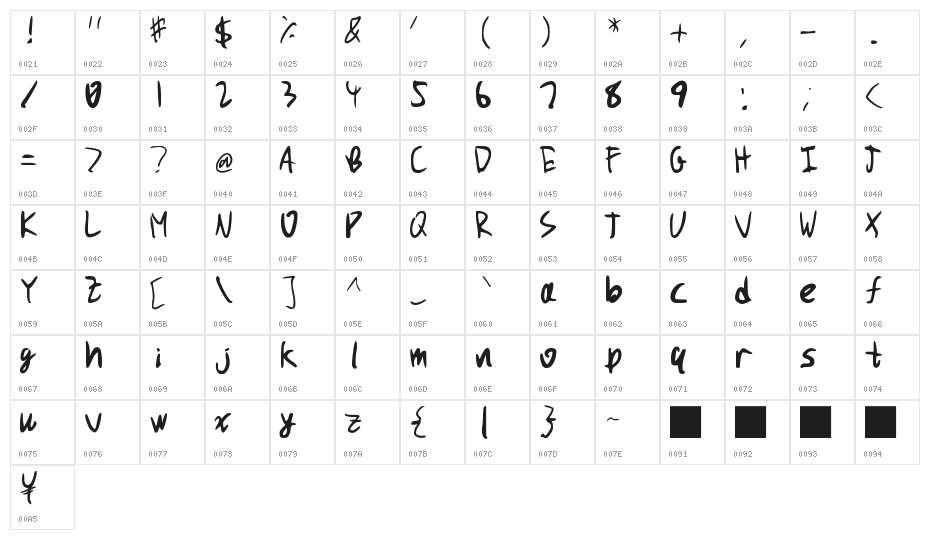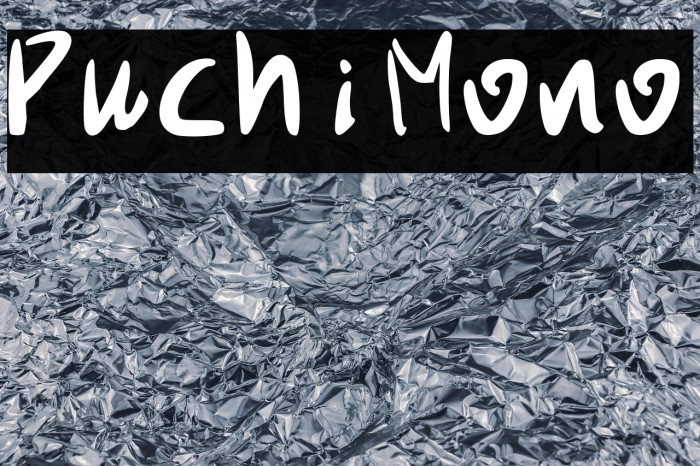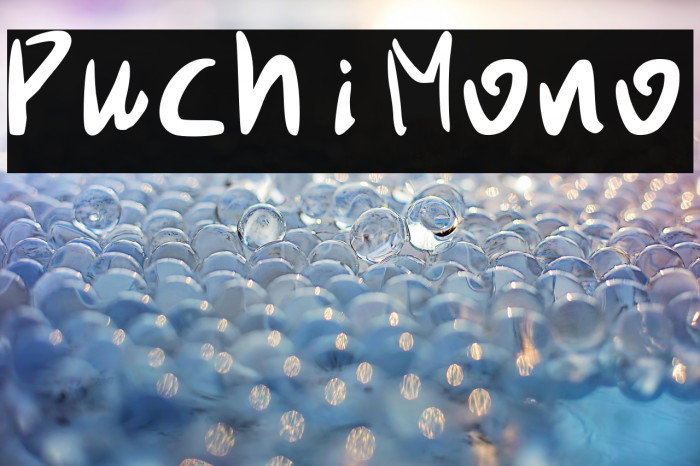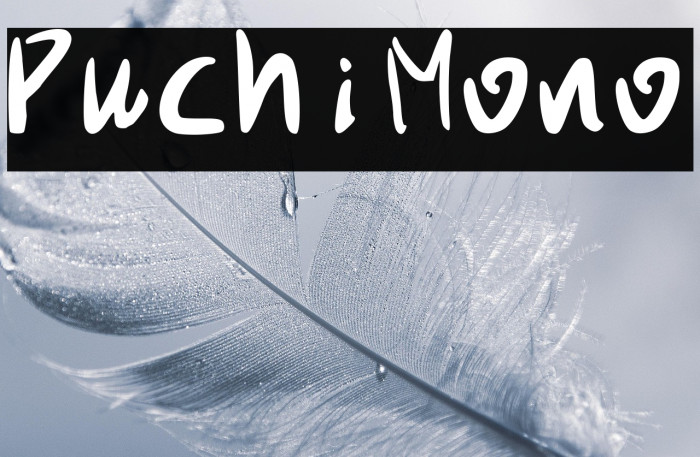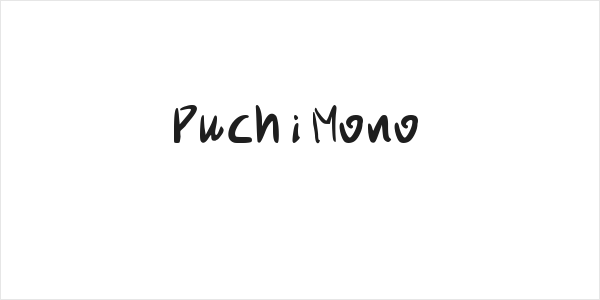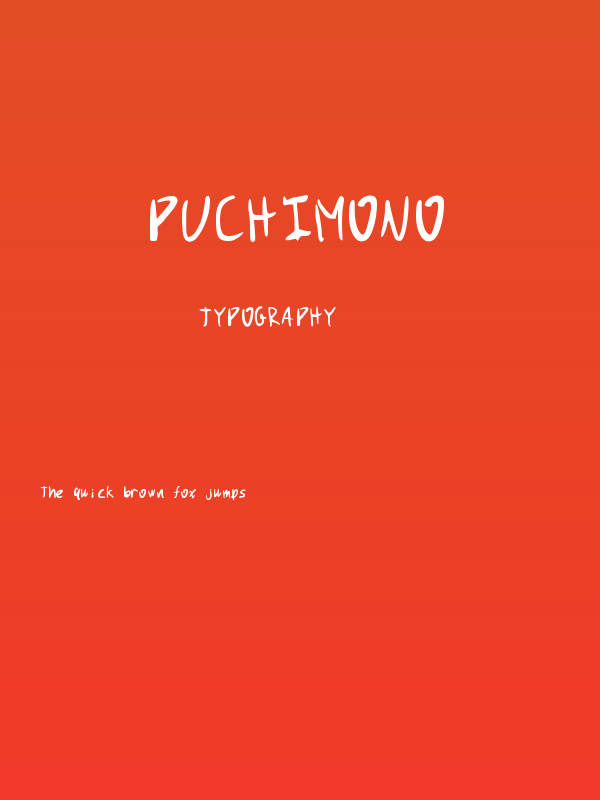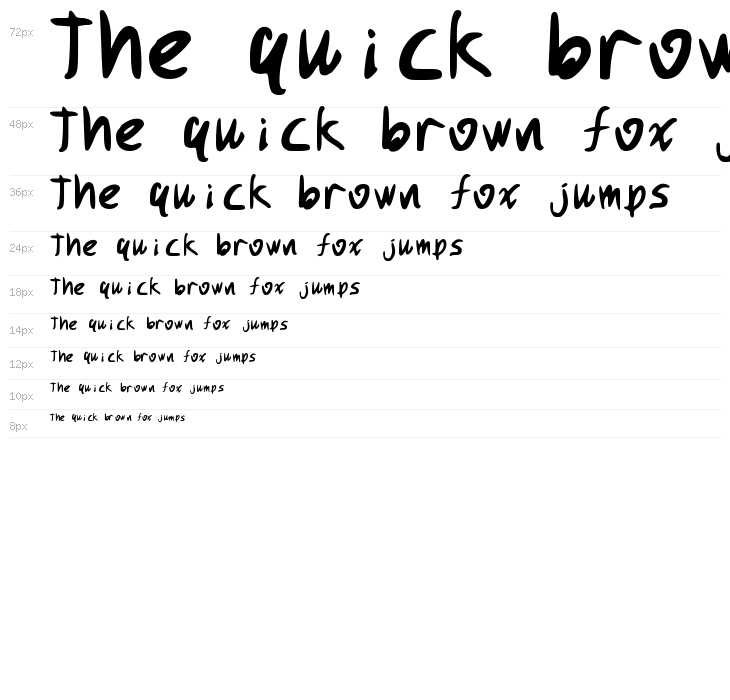
PuchiMono Font
| Zeichenabstand | Normal |
| Gesamtstil | Casual |
| Anwendungsfall | Headlines, Informal texts, Creative projects |
| Vorgeschlagene Projekte | Ideal for greeting cards, children's books, casual branding, and social media graphics. |
| Wird Pitch | Yes |